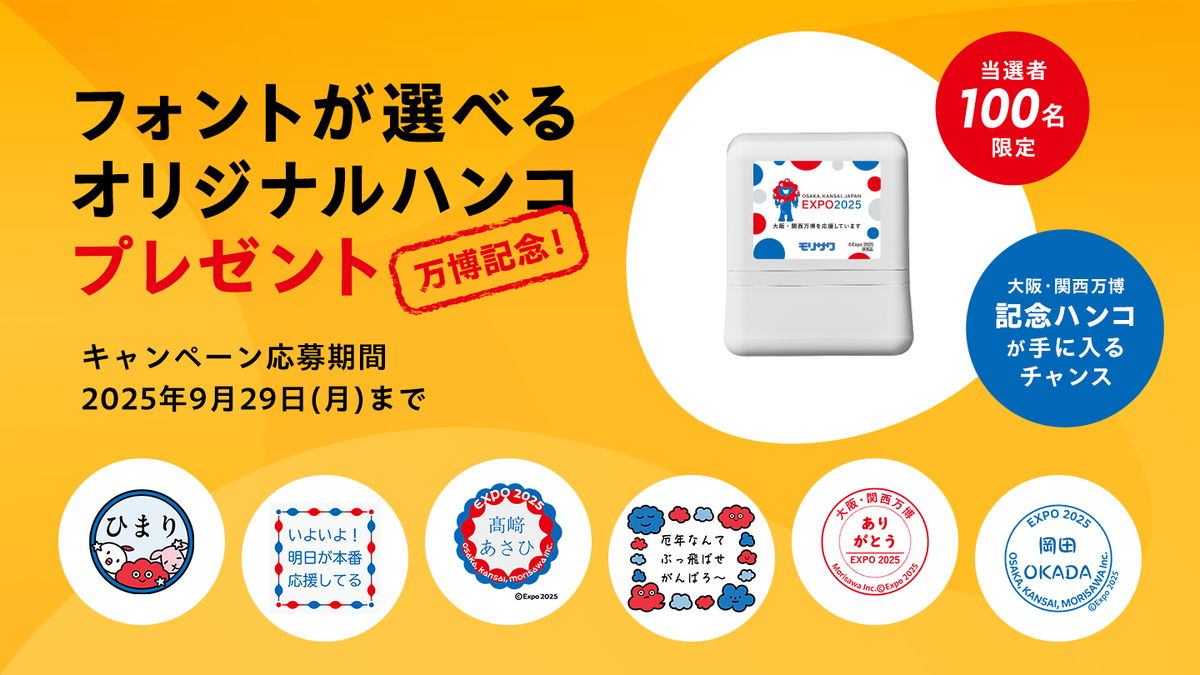
大阪・関西万博記念で好きな言葉&デザイン&フォントでデジタルスタンプが作れる特設サイト「フォント de スタンプ」公開。ミャクミャクデザインのハンコが当たるキャンペーンも同時開催
モリサワは、2025年日本国際博覧会(以下、大阪・関西万博)において「大阪・関西万博PRブロンズパートナー」として協賛していることを記念し、大阪・関西万博特設サイトを開設、フォントを選んで作れる!「フォント de スタンプ」を公開した。
フォントを選んで作れる!「フォント de スタンプ」は、大阪・関西万博モチーフのデザインを含むフレーム(台紙)とモリサワのフォントを使って、自分自身の好きな言葉や名前を入力したオリジナルデジタルスタンプ(スタンプ形式のデジタル画像)を作成、ダウンロードでき、フォントを変えることで言葉の印象が変わる楽しさを体験できる。
ダウンロードしたデジタルスタンプは、電子印鑑として使うのはもちろん、SNSのアイコンや写真、メッセージカードに加工するなど自由に利用できる。
また、作成したデジタルスタンプが、本物のハンコになって届く「万博記念!フォントが選べるオリジナルハンコプレゼント」キャンペーンも実施。
ハンコのハンドル部分は、大阪・関西万博の公式キャラクターミャクミャクのデザインとなっており、世界に一つだけのオリジナル万博グッズになるかもしれない。
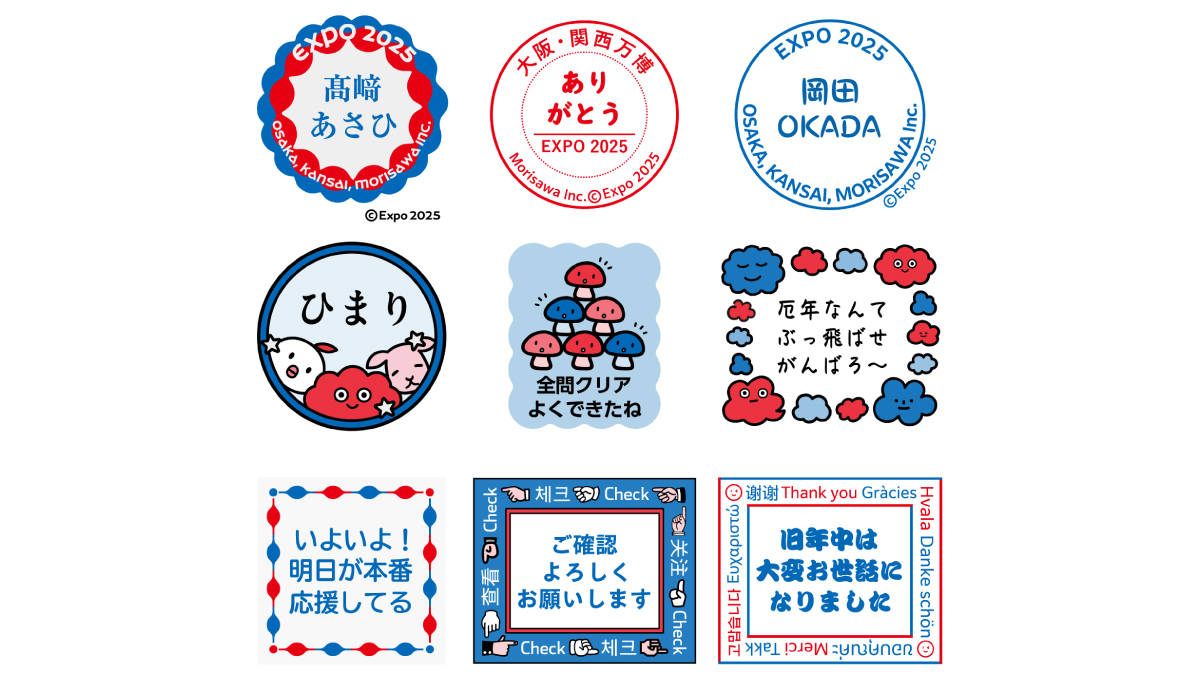
▼フォントを選んで作れる!「フォント de スタンプ」
フォントを選んで作れる!「フォント de スタンプ」のフレーム(台紙)デザインは全部で9種類、期間限定で大阪・関西万博モチーフのデザインを選ぶこともできる。
選べる12種類のフォントは、モリサワの代表的なユニバーサルデザイン(UD)フォントで、大阪・関西万博の会場サインなどに協賛で提供している「UD新ゴ」や、推し活うちわの文字などで人気の高い「勘亭流」、ビジネスシーンでも使用頻度の高い「正楷書CB1」、教育現場でも注目されている「UDデジタル教科書体」や「UD学参丸ゴシック」、近年人気の手書き風フォント「ぺんぱる」などで、自分にぴったりのオリジナルデジタルスタンプを作成することができる。
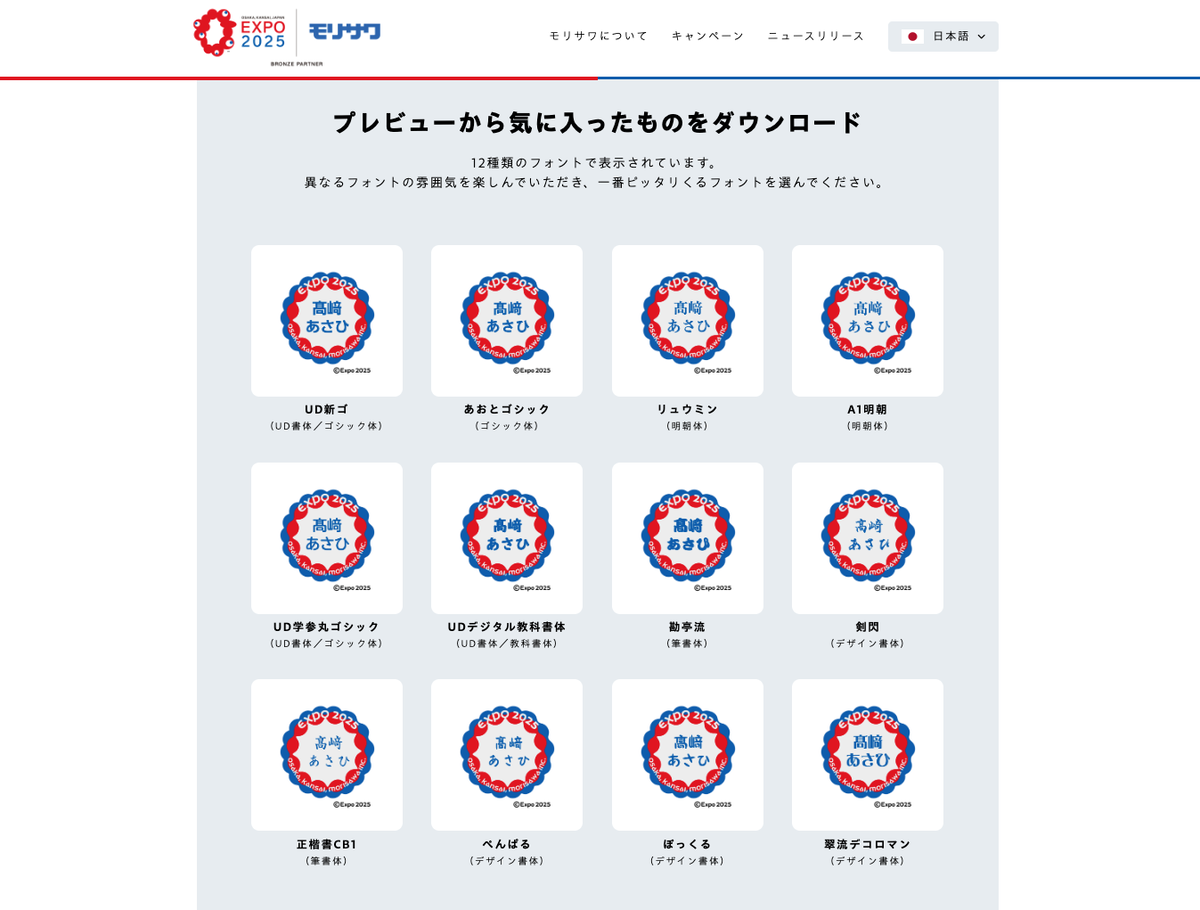
「万博記念!フォントが選べるオリジナルハンコプレゼント」キャンペーンについて
フォントを選んで作れる!「フォント de スタンプ」でデジタルスタンプを作成し、応募した人の中から抽選で100名に、「万博記念!フォントが選べるオリジナルハンコ」をプレゼントするキャンペーン。
「万博記念!フォントが選べるオリジナルハンコプレゼント」キャンペーン
プレゼント内容:応募作品をもとに制作した「万博記念!フォントが選べるオリジナルハンコ」
ハンコのハンドル部分は、大阪・関西万博の公式キャラクターミャクミャクをあしらったデザイン
モリサワ大阪・関西万博特設サイトについて
「フォントの世界へようこそ クイズで学び、スタンプで遊ぼう」と題して、文字の力で大阪・関西万博を盛り上げる特設サイト。フォントを選んで作れる!「フォント de スタンプ」のほか今後は、クイズ王伊沢拓司氏が率いる知的エンタメ集団「QuizKnock」とコラボレーションしたフォントのクイズも公開予定。
モリサワと大阪・関西万博について
モリサワは「大阪・関西万博PRブロンズパートナー」として協賛し、大阪・関西万博の会場サインやアプリなどで使用するための各種フォントも提供している。また、「大阪ヘルスケアパビリオン Nest for Reborn」のサポーターとして、展示ディスプレイや平面サインなどで使用されるフォントを提供しているほか、その他のパビリオンでも各種フォントを採用している。